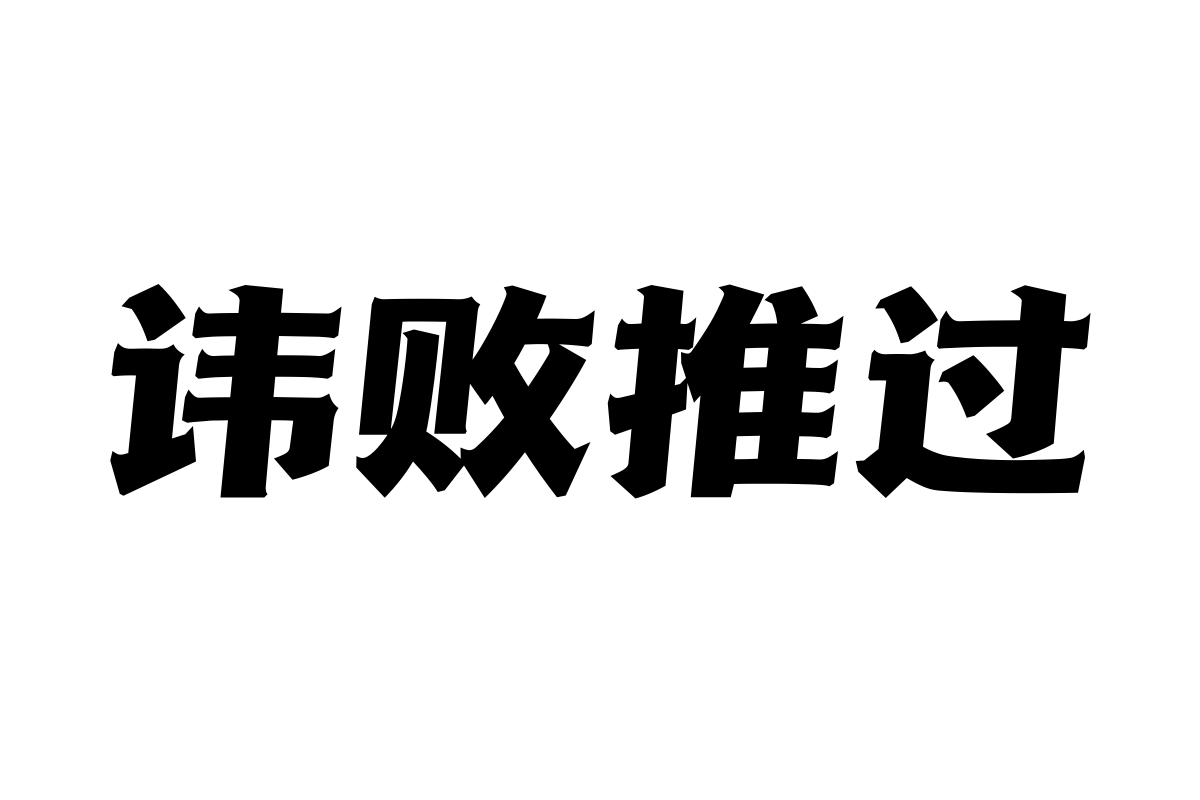
汉仪霸蛮体是一款具有强烈个性和独特风格的字体,其特点是笔画粗犷、结构紧凑、形态夸张。这种字体适合用于需要突出个性和创意的场合,如广告设计、包装设计、标志设计等。汉仪霸蛮体的特点是笔画粗细变化明显,给人一种强烈的视觉冲击力。同时,它的结构紧凑,使得整体看起来更加简洁有力。此外,汉仪霸蛮体还具有一定的可读性,适用于需要清晰表达信息的场合。总的来说,汉仪霸蛮体是一款非常独特且富有创意的字体,适合用于需要强调个性和创意的场合。
汉仪霸蛮体